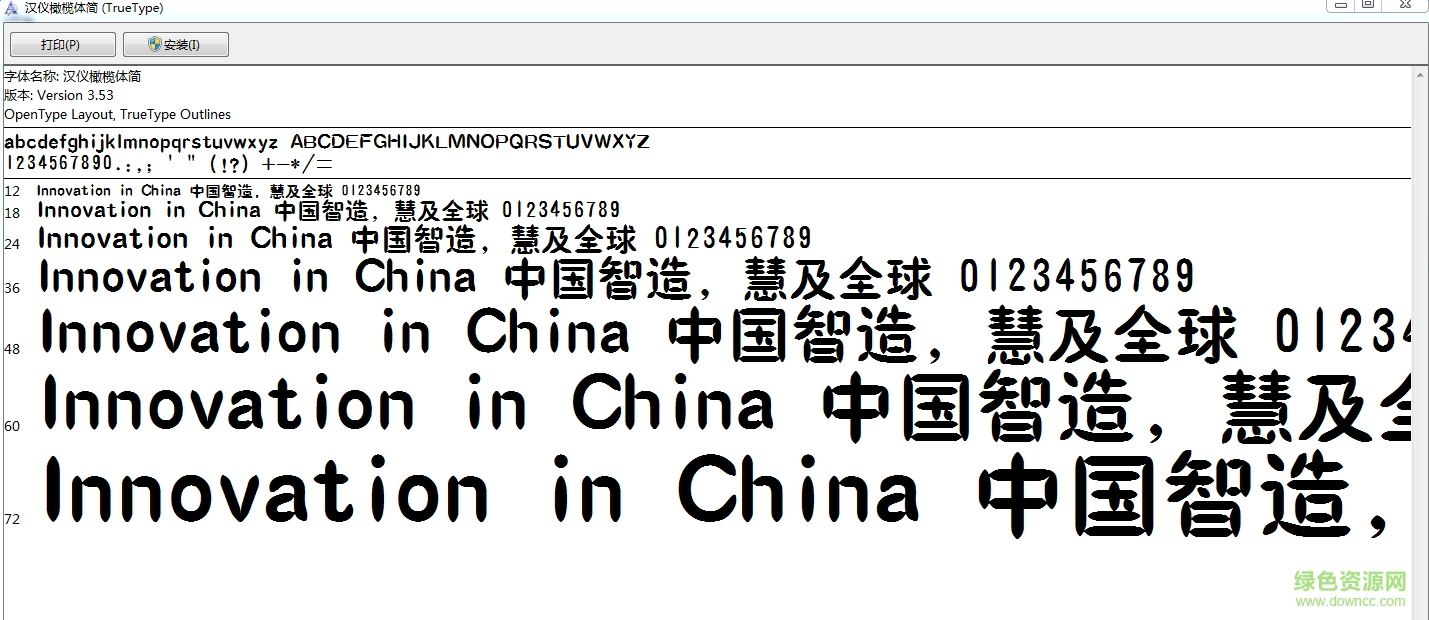
hyx1gj字體又稱漢儀橄欖體簡(jiǎn),是漢儀打造的一款非常有特色的電腦字體,字形粗獷顯眼,適用于美工設(shè)計(jì)方面,感興趣的朋友歡迎來(lái)綠色資源網(wǎng)下載安裝!
hyx1gj字體簡(jiǎn)介
hyx1gj字體是一款應(yīng)用于設(shè)計(jì)方面的中文簡(jiǎn)體漢字,該字體以橄欖為原形而設(shè)計(jì),線條粗壯,大方得體,并且整體效果十分出色,可以應(yīng)用于廣告設(shè)計(jì)、名片設(shè)計(jì)、包裝印刷、產(chǎn)品設(shè)計(jì)等應(yīng)用!